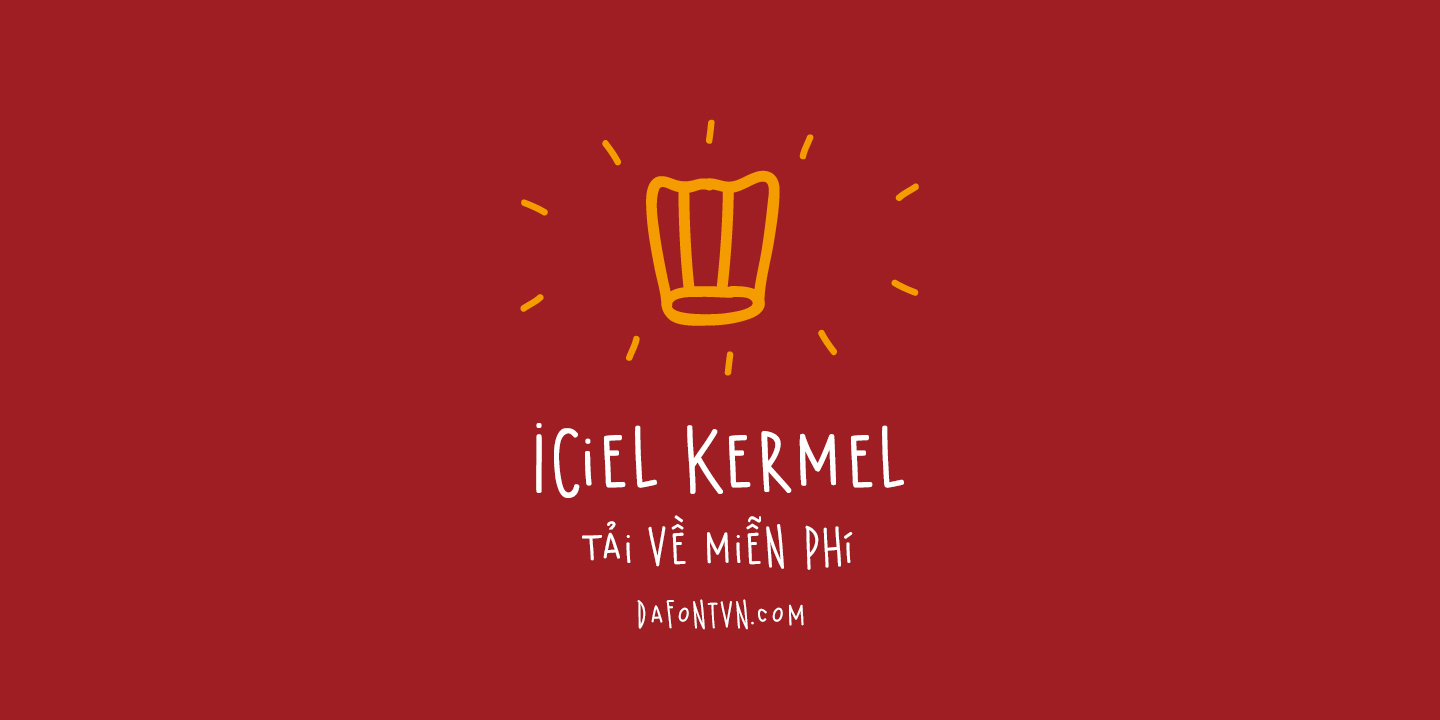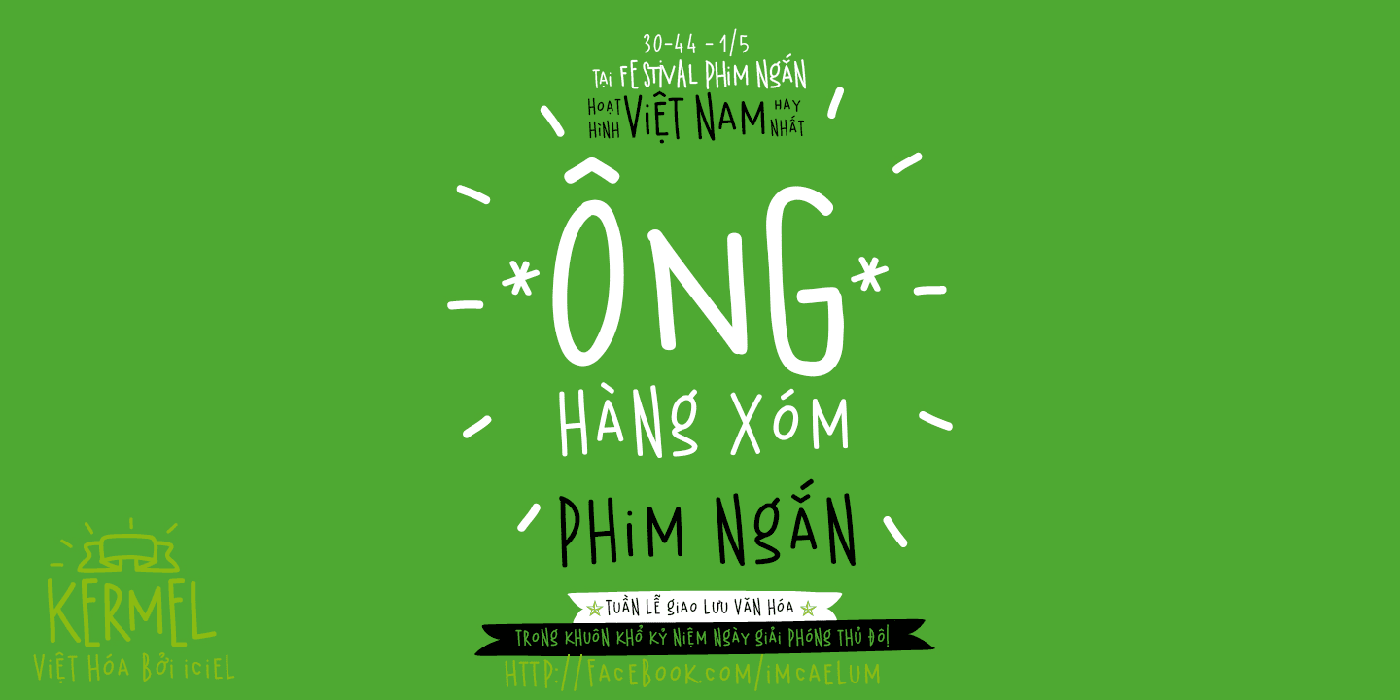
Tải font iCiel Kermel Việt Hóa miễn phí Phần Mềm Gốc 10 Tháng 05 năm 2024 0 0 687 iCiel Kermel là một font chữ dạng viết tay khá đẹp đã được Việt Hóa, phù hợp để sử dụng trong thiết kế tiêu đề, văn bản ngắn, logo.Giấy phép: Chỉ sử dụng cá nhân Định dạng miễn phí: TTF Tổng số tệp: 2Bài viết liên quan: Tải trọn bộ font Philosopher Việt hóa (4 font) 10 Tháng 05 năm 2024 Font DT Phudu – Font chữ phong cách xưa cũ 10 Tháng 05 năm 2024 Font Valky Việt hóa v2 – Kiểu font hiện đại, cổ điển 10 Tháng 05 năm 2024